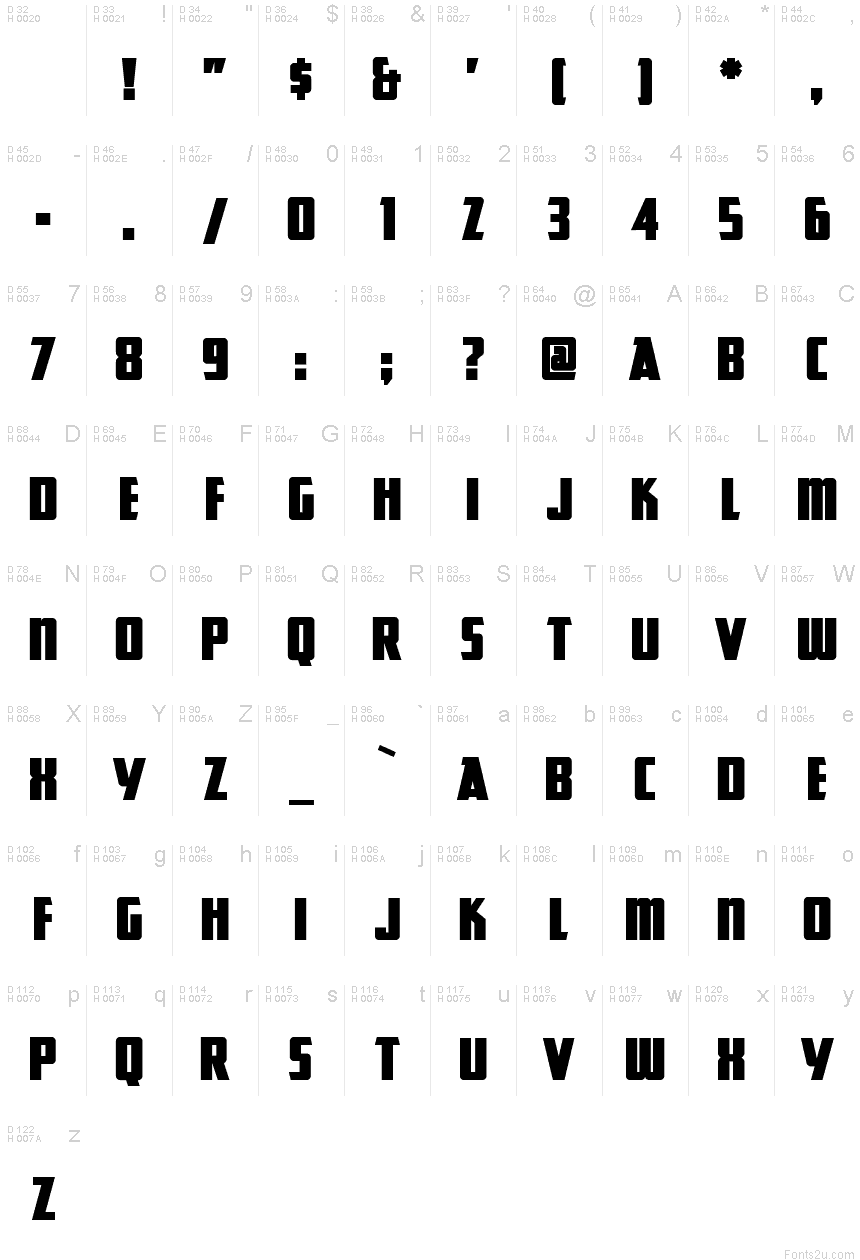
Great Lakes NF autorstwa Nicka Curtisa to darmowy krój retro typu display, który uderza z siłą billboardu z czasów świetności ręcznie malowanych szyldów. Masywne litery, ciasne światła i kanciaste krzywizny tworzą solidną ścianę atramentu – surową, głośną i wyrazistą. Rytm jest zwarty i przemyślany, dzięki czemu każde słowo pasuje do kolejnego niczym stos drewnianych skrzyń. To idealny wybór, gdy potrzebujesz nagłówka, który nie szepcze, lecz krzyczy.
Dzięki Great Lakes NF nadasz mocnego charakteru plakatom, identyfikacji wizualnej sportowych marek, logotypom, opakowaniom, szyldom, okładkom albumów i banerom eventowym. Ten darmowy font świetnie sprawdza się w krótkich hasłach i dużych napisach, gdzie jego ciężkie kształty mogą w pełni wybrzmieć. W przypadku tekstów ciągłych połącz go z prostym krojem bezszeryfowym (groteskiem) lub geometrycznym sans-serifem i pozwól Great Lakes NF przejąć najważniejsze linie w dużych rozmiarach.